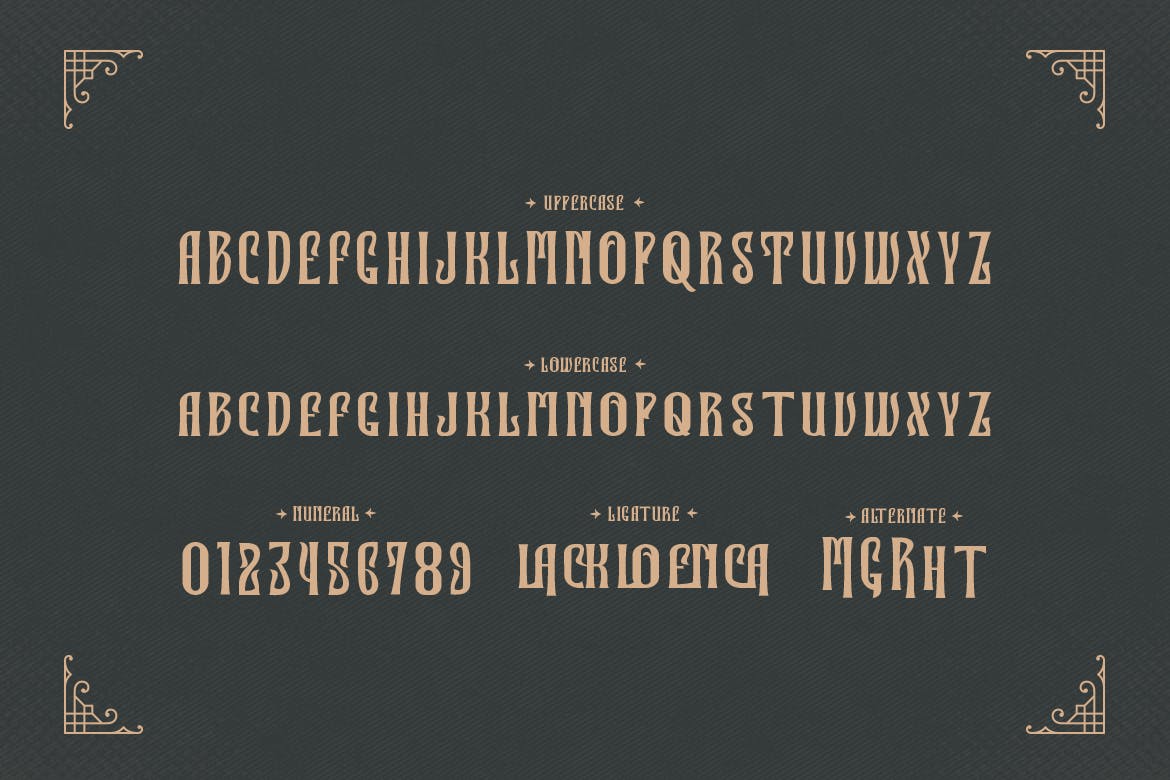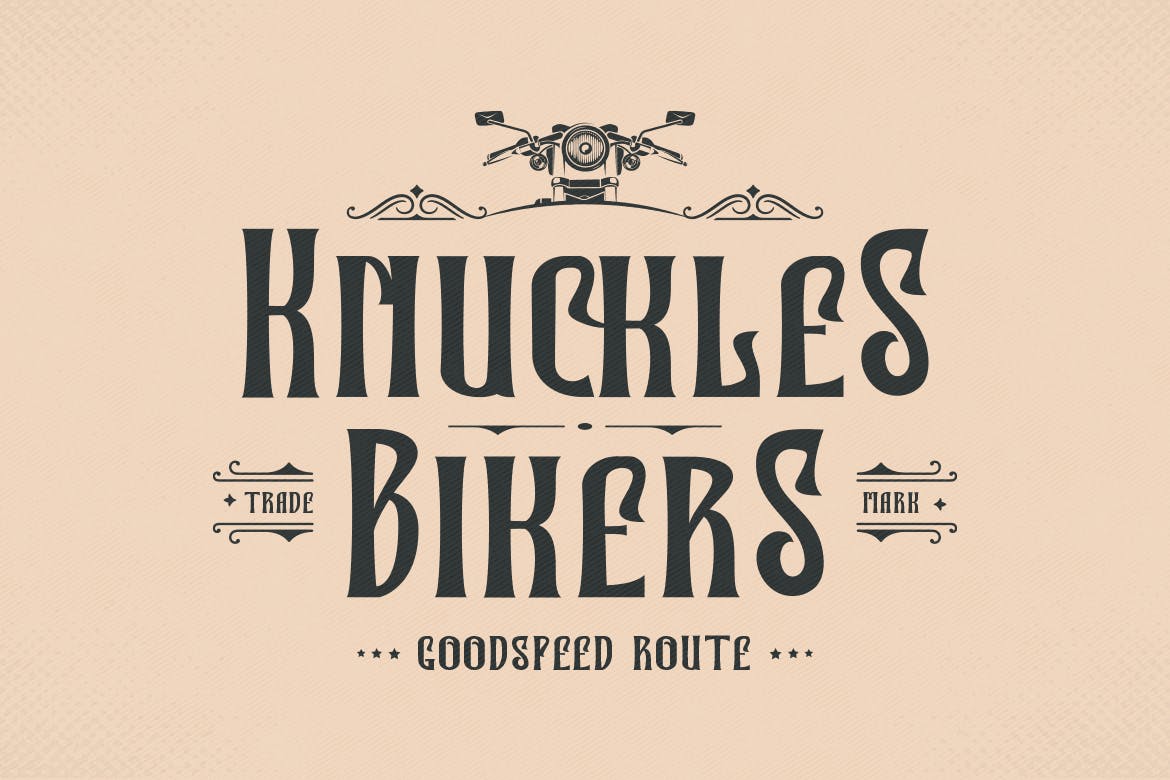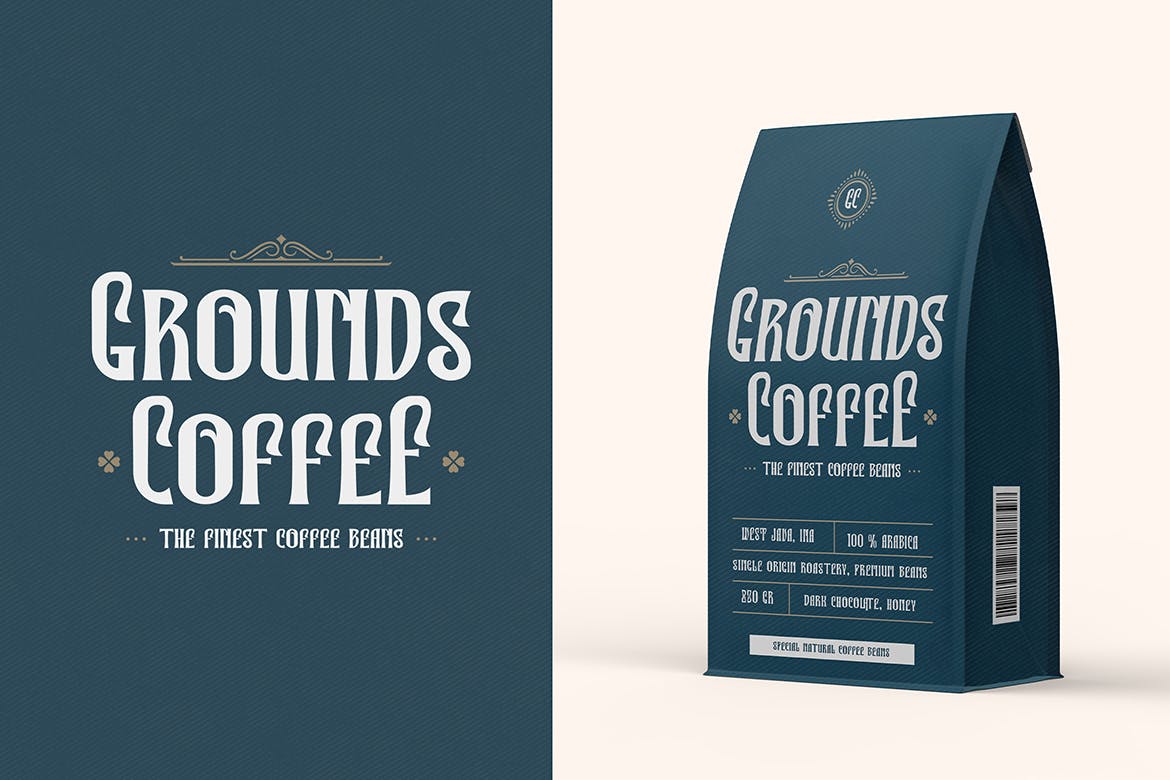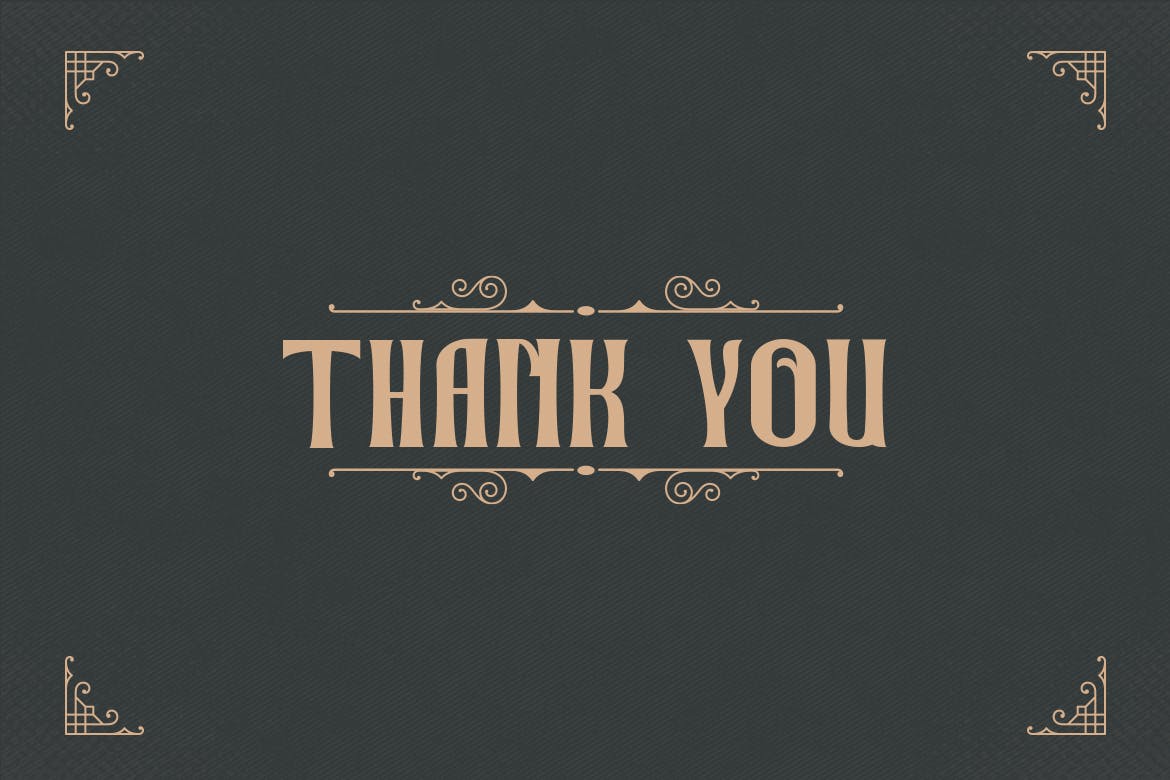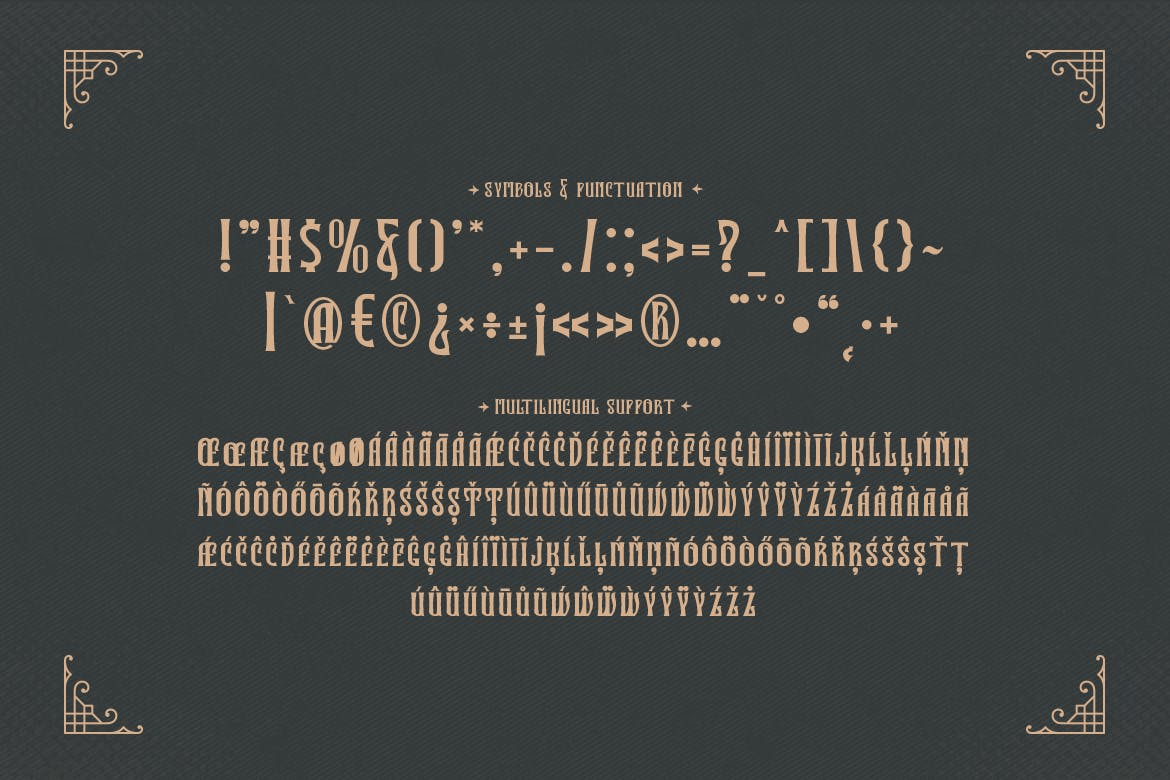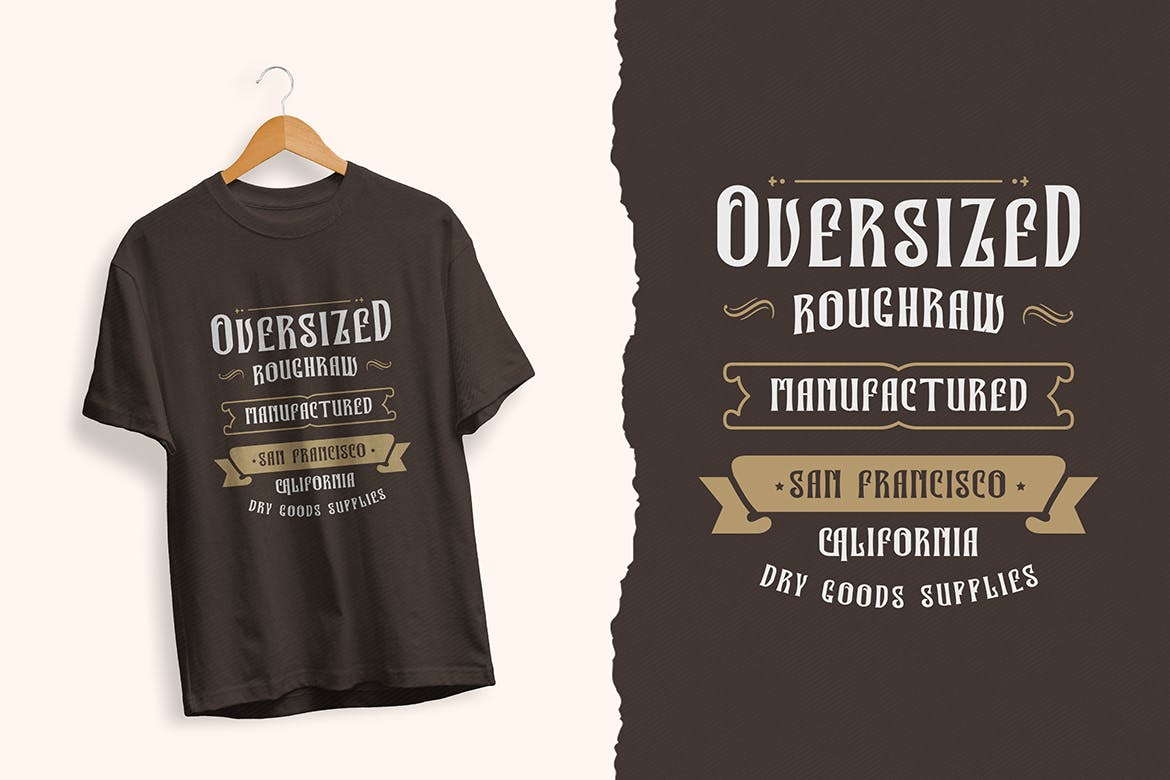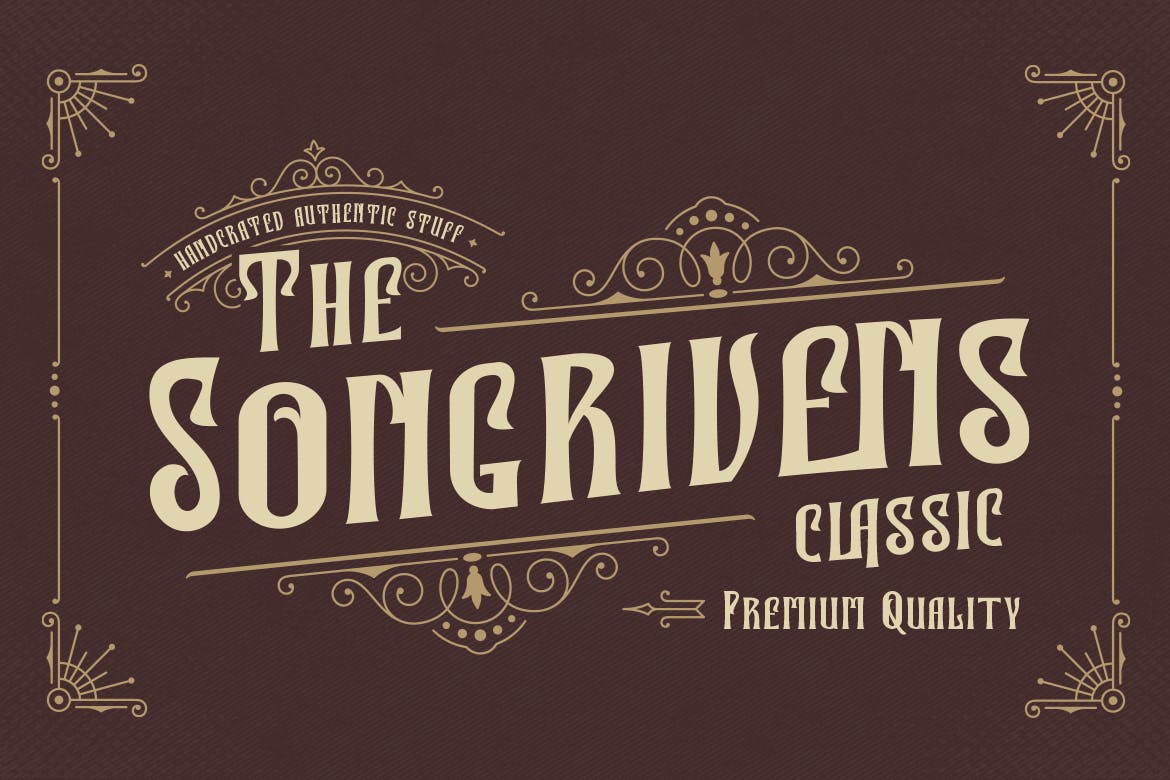
Reinbrow Vintage Display Font
فونت Reinbrow، انتخابی عالی برای طراحی‌های وینتج و مدرن شماست.
فونت Reinbrow یک فونت نمایش وینتج است که برای استفاده در پروژه‌های مختلف طراحی شده است. این فونت مناسب برای طراحی لوگوها، عناوین، کافه‌ها، رستوران‌های وینتج، سرنامه‌ها، تابلوها، برچسب‌ها، اخبار، پوسترها، نشان‌ها و بسیاری موارد دیگر می‌باشد.
ویژگی‌ها:
• حروف بزرگ
• حروف کوچک
• نمادها و نشانه‌گذاری
• اعداد
• لیگاتورها
• نسخه‌های جایگزین
• پشتیبانی چند زبانه